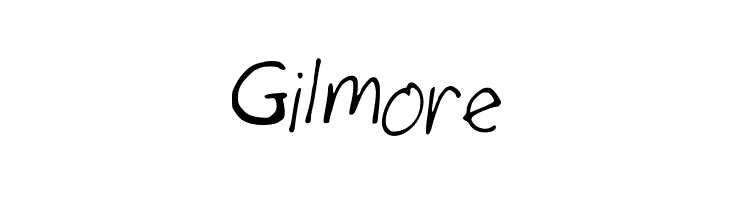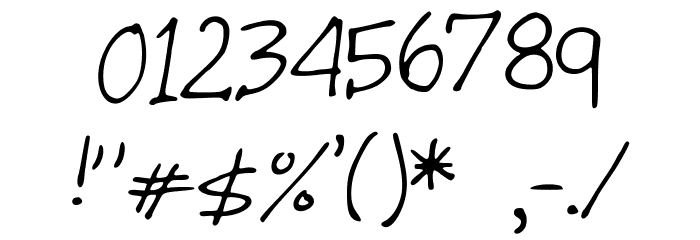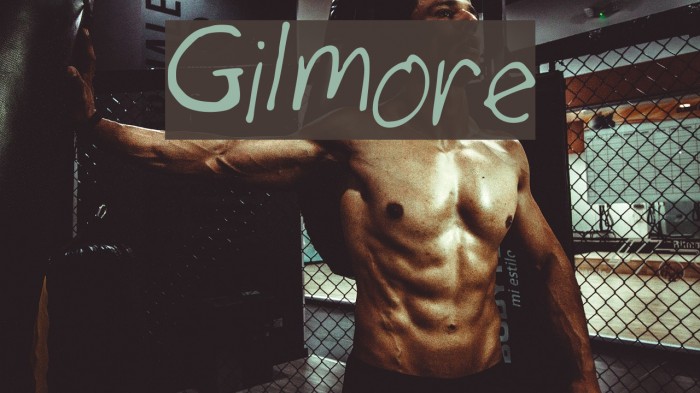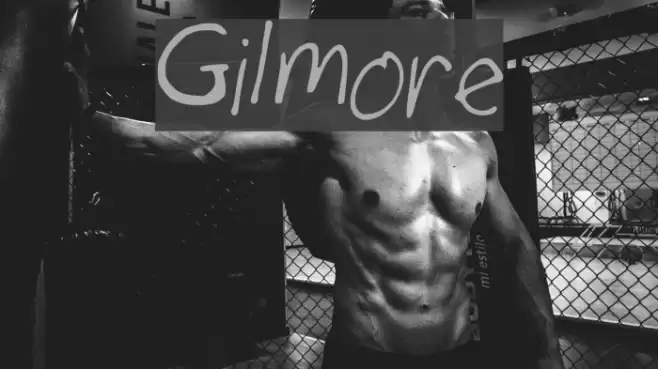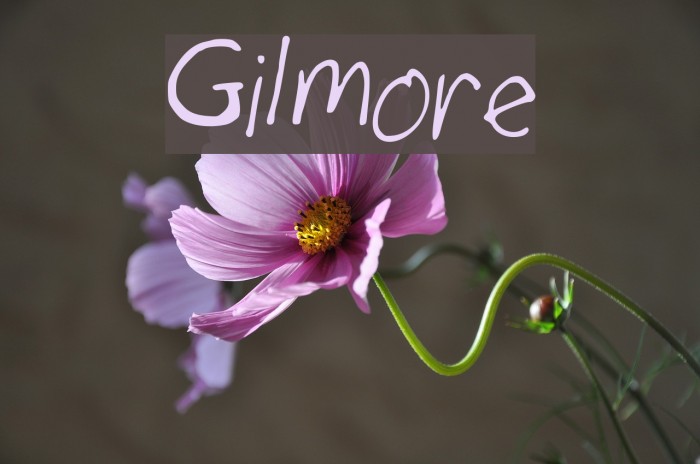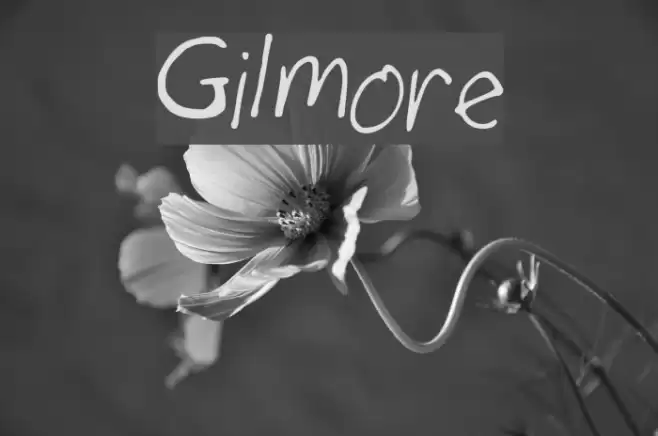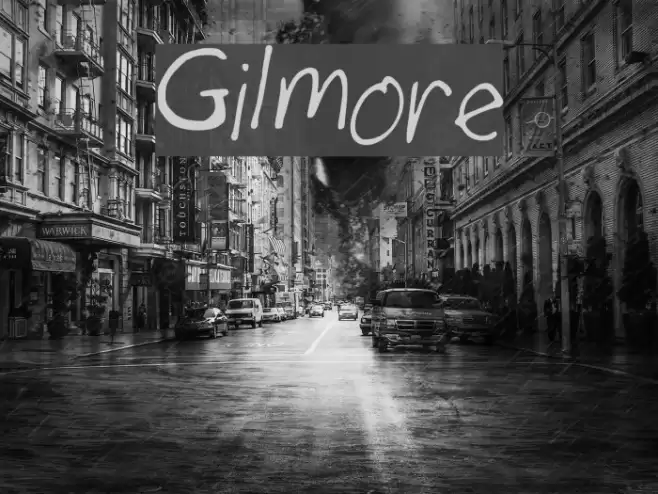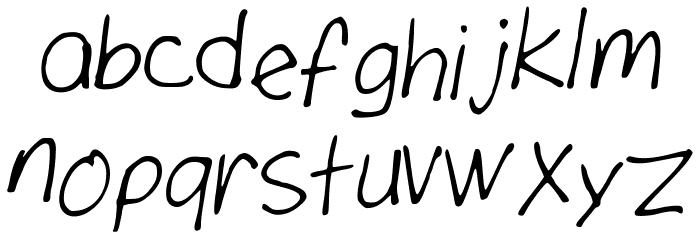
Gilmore Font
| 全体的なスタイル | Casual |
| 用途 | Headlines, Logos, Informal Text |
| おすすめプロジェクト | Ideal for greeting cards, invitations, personal branding, and creative projects that require a friendly and approachable touch. |